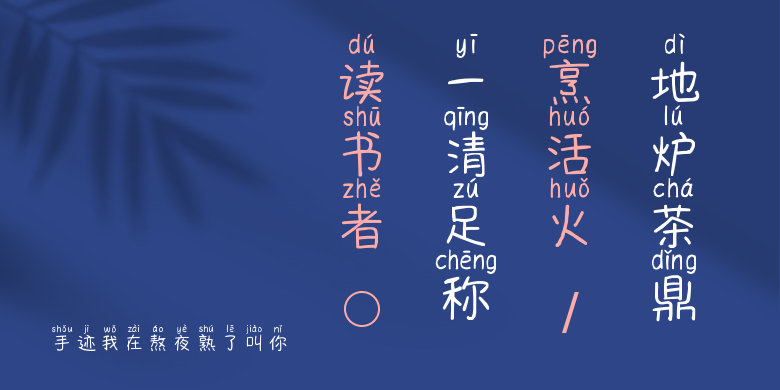
手迹我在熬夜熟了叫你
手迹我在熬夜熟了叫你,这款字体结构工整、笔画清晰,兼顾美观与易读性,适用于标题、正文、海报、包装、LOGO 等多种场景。字形优雅稳定,风格百搭耐看,适配日常排版与创意设计,让文字呈现更舒适、更具质感。手迹我在熬夜熟了叫你一笔一画,皆是细节,以均衡的比例、流畅的线条打造舒适视觉体验,字形端正大气,风格简约现代。无论是商业设计、品牌宣传还是日常排版,都能轻松驾驭,让文字更有格调与力量。手迹我在熬夜熟了叫你字体下载。